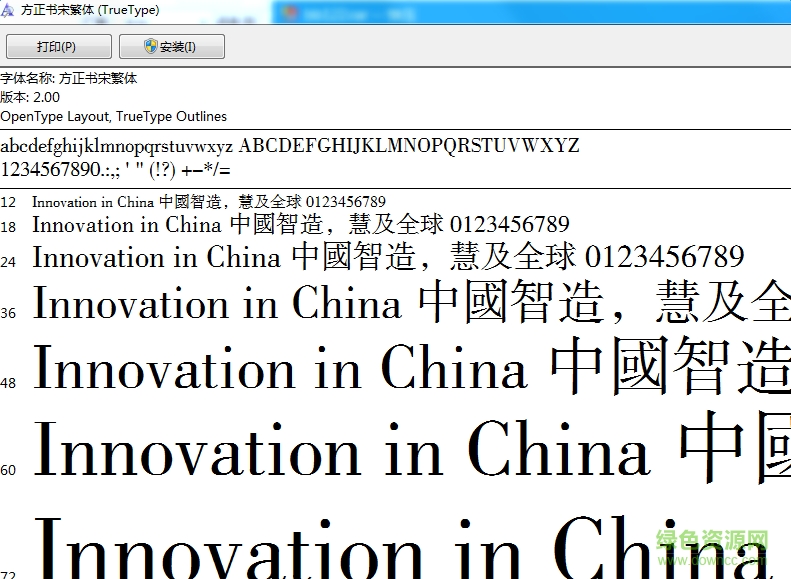
軟件介紹 軟件標簽: 宋體繁體 宋體 宋體繁體字體大全收錄了方正書宋繁體、金山繁標宋體、微軟繁宋體、長城書宋體繁、創(chuàng)藝繁宋體等一系列宋體,字面大小勻稱,線條剛柔并濟,適合用于排版設計,歡迎大家在綠色資源網下載!宋體溯源宋體字名為宋體,其實誕生在明朝,而其根本原因是明清兩代文人仰慕宋朝文化、追捧宋刻本所致。到乾隆時期,宋體字已大體定型,其橫畫收筆的三角、豎畫起筆的三角等,與現(xiàn)代宋體字基本相同。宋體推薦漢呈水墨中國風字體 ttf版授權:免費軟件 WinAll, WinXP, Win7大?。?.4M語言:中文漢呈水墨中國風字體免費版是漢呈王天喜系列相關的一款字體,在原來的基礎上添加了一個水墨風格的圓圈,字形看起來比較渾厚圓潤,充滿水墨中國風特色,極具個性,是很多用戶常用的藝術手寫字體,適用于多個不同的設計下載地址小塚宋體 簡體 授權:免費軟件 WinAll大?。?.4M語言:中文小冢宋體等寬字體是一款繁體的宋體字體,該字體橫輕豎重,字形標準,古韻十足,適合用作書面字體或電腦排版字體,歡迎大家在綠色資源網免費下載這款繁體字體!宋體介紹現(xiàn)代鉛字主要采用宋體印刷。后來依據(jù)西方文字的下載地址宋體繁體安裝說明1.在綠色資源網下載字體包,并解壓縮2.最簡單的安裝方法:雙擊字體文件,點擊安裝按鈕即可2.批量安裝方法:將字體文件放到C:\Windows\Fonts 軟件截圖 上一張下一張(1 / 1) 安裝詳細截圖 猜你喜歡 宋體字體 宋體字體 宋體是目前最常用的一款漢字字體,宋體成型于明朝,歷史悠久,字體特點是橫細豎粗,線條平直,結構嚴謹,工整又不失大氣,非常適用于文字排版方面! 查看更多>> 原版宋體 5.37M/中文/1.4/下載 繁體宋體字體打包 14.64M/中文/2.5/免費版下載 經典中宋繁 regular 3.26M/中文/5.0/下載 粗標宋體 2.44M/中文/5.0/下載 方太夢想宋字體(中/細/粗體) 6.36M/中文/2.5/非商用下載 宋體-亮體(chinese-gb2312) 5.85M/中文/5.0/下載 其他版本下載 標題 大小 更新日期 下載 下載地址 電腦版 繁體宋體字體打包 免費版 點擊報錯 軟件無法下載或下載后無法使用,請點擊報錯,謝謝! 關閉報錯反饋 請描述您所遇到的錯誤,我們將盡快予以修正,謝謝! *必填項,請輸入內容 本類最新 dreamweaver字體庫 首爾南山體字體 v1.06 官方版 潮字社風云簡ttf 潮字社凌渡鯤鵬簡體字體 潮字社曾玉波手書簡字體 微博慧心字體 相關文章 Photoshop字體安裝使用方法和技巧 Win 7系統(tǒng)安裝字體方法 網頁字體大小設置方法 怎么改網頁字體大小 在Linux系統(tǒng)中安裝字體的幾種方法 windows7字體顯示問題:打開某些程序的時候顯示的是亂碼 Windows7安裝字體和用快捷方式安裝字體 用戶評論 熱門評論 最新評論 發(fā)表評論 查看所有評論(0) 昵稱: 請不要評論無意義或臟話,我們所有評論會有人工審核. 字數(shù): 0/500 (您的評論需要經過審核才能顯示)